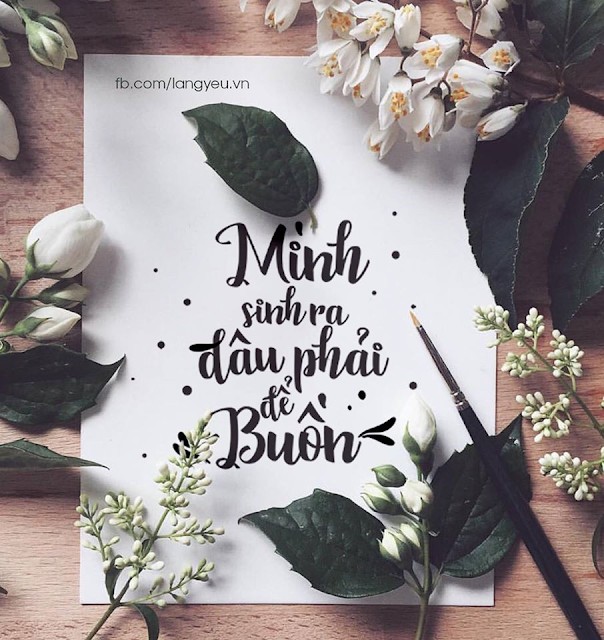
Tải Font việt hóa LNTH Jaiho Script Miễn Phí Cho Thiết Kế Ấn Tượng
Trong thế giới đồ họa hiện đại, việc tìm kiếm một bộ Font Chữ độc đáo để thể hiện cá tính riêng là điều vô cùng quan trọng đối với các bạn học sinh và giáo viên. Font việt hóa LNTH Jaiho Script nổi lên như một lựa chọn hàng đầu nhờ sự kết hợp tinh tế giữa phong cách thư pháp hiện đại và nét vẽ thanh thoát. Đây là bộ font không chỉ đẹp về mặt thị giác mà còn mang lại cảm giác gần gũi, giúp các bài thuyết trình hay báo tường trở nên sinh động và cuốn hút hơn bao giờ hết.
Khám phá vẻ đẹp đặc trưng của Font việt hóa LNTH Jaiho Script
Phong cách thiết kế điệu đà và linh hoạt
Font việt hóa LNTH Jaiho Script sở hữu những đường nét uốn lượn mềm mại, mô phỏng lại nét bút lông thủ công một cách chân thực. Sự linh hoạt trong các nét nối chữ giúp bộ font này tạo nên một dòng chảy tự nhiên, khiến văn bản trở nên nghệ thuật như một bức tranh chữ. Đặc biệt, phiên bản việt hóa đã được tối ưu hóa hoàn toàn các dấu câu tiếng Việt, đảm bảo không bị lỗi hiển thị khi soạn thảo trên các phần mềm thiết kế phổ biến hiện nay.
Ứng dụng đa dạng trong học tập và sáng tạo
Nhờ vẻ ngoài thanh lịch, bộ font này cực kỳ phù hợp để thiết kế tiêu đề bài học, thiệp chúc mừng thầy cô hoặc các poster sự kiện trường lớp. Độ tương phản giữa các nét thanh và nét đậm giúp chữ dễ đọc nhưng vẫn giữ được sự sang trọng cần thiết cho các ấn phẩm sáng tạo.
Cách sử dụng Font việt hóa LNTH Jaiho Script hiệu quả
Để phát huy tối đa vẻ đẹp của font, bạn nên kết hợp nó với các tông màu pastel hoặc màu nước nhẹ nhàng. Việc sử dụng font làm điểm nhấn cho các câu trích dẫn hay tiêu đề chính sẽ tạo ra sự chuyên nghiệp cho tác phẩm. Hãy trải nghiệm ngay Font Miễn Phí, Font Việt Hóa, Font việt hóa LNTH Jaiho Script để biến những ý tưởng thiết kế của bạn thành hiện thực một cách hoàn hảo nhất.